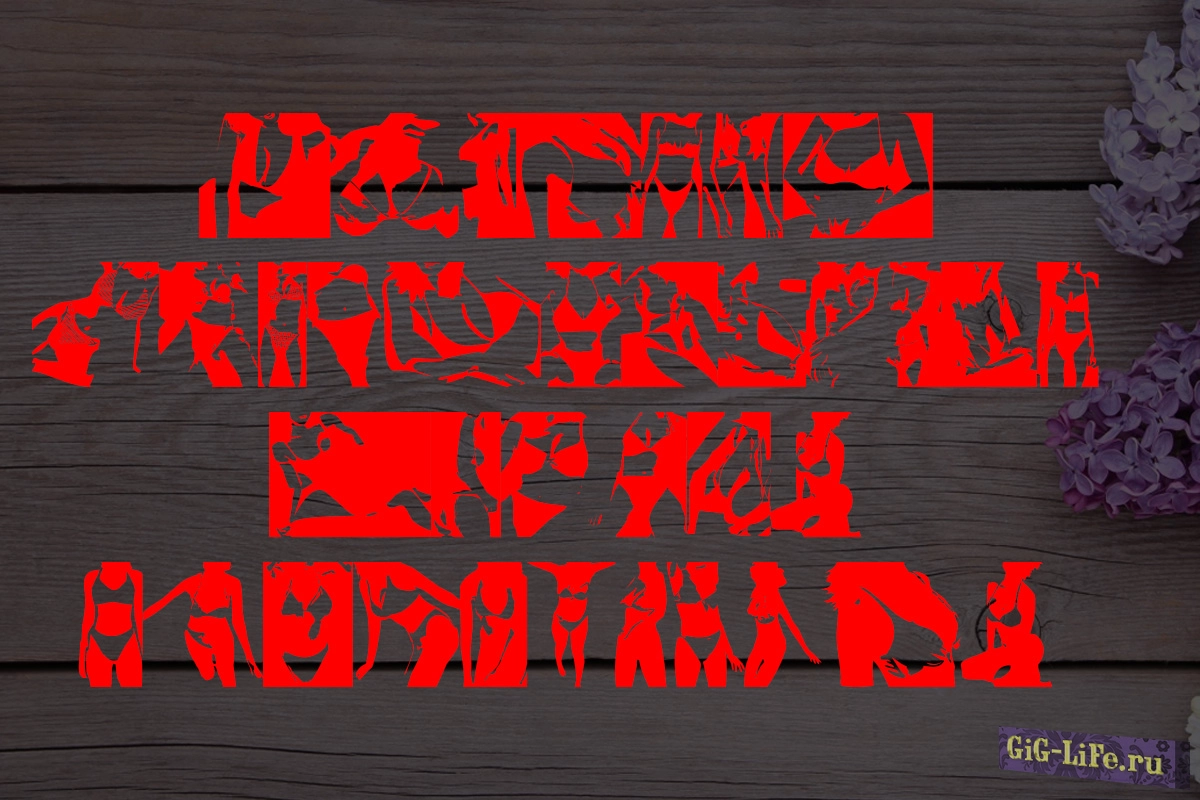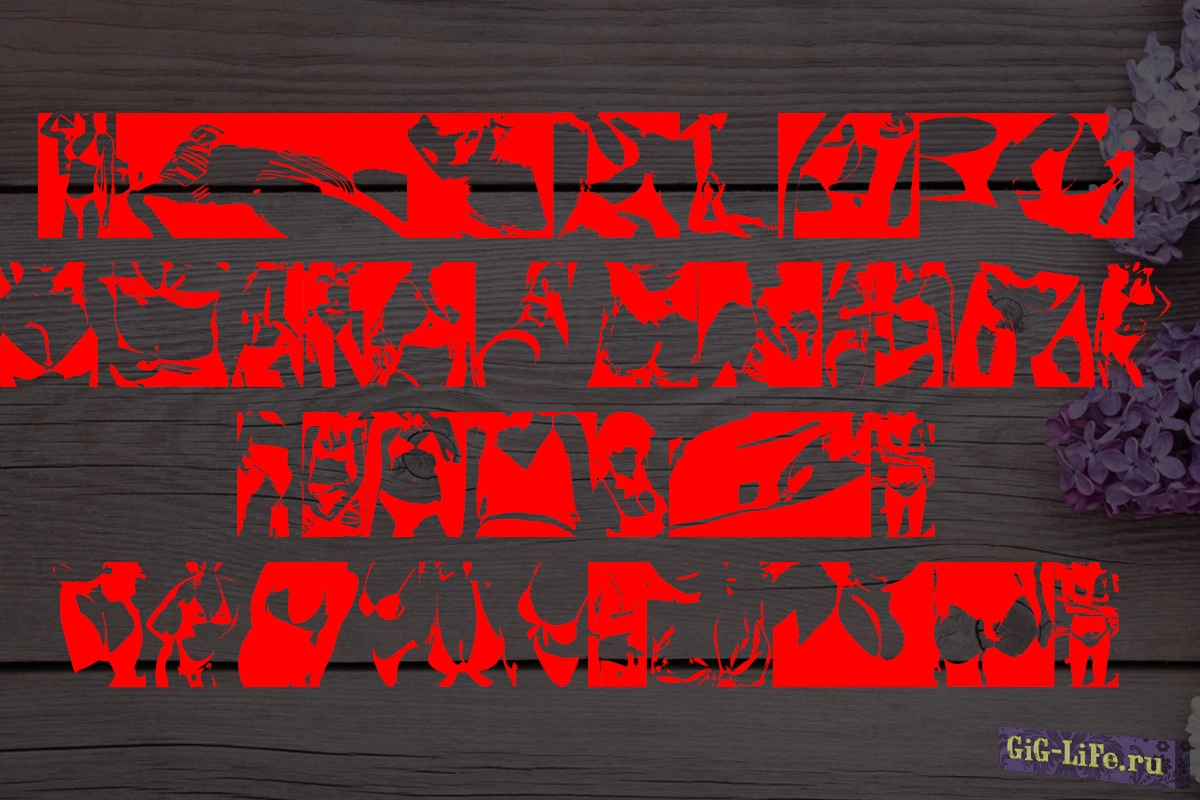
SexyDynamite №2, второй эротический шрифт, предназначенный для использования в программе Photoshop и других творческих проектах, создан на основе символов.